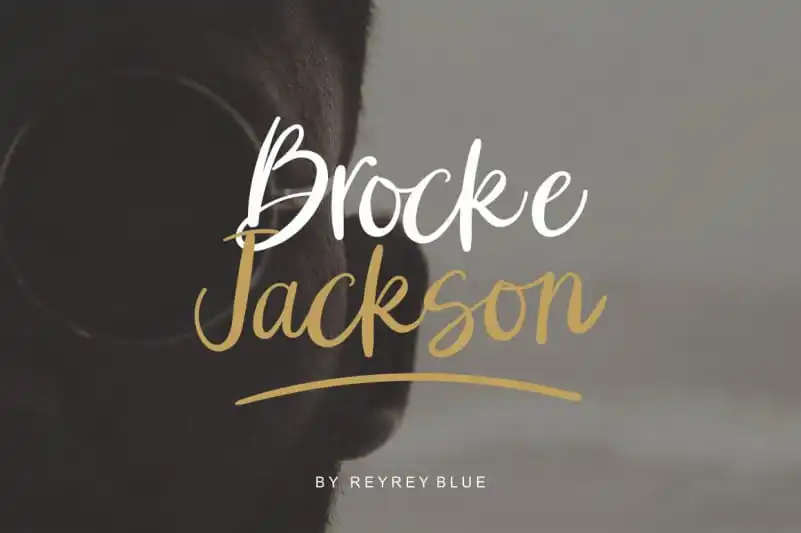
Brocke Jackson Script Font – Download Grátis
Brocke Jackson Script Font é uma elegante escolha para aqueles que buscam personalidade e elegância no seu design tipográfico. Desenvolvida pelo designer ReyreyBlue, esta fonte escritura expressa tem um toque de frescor ao combinar uma caligrafia cuidadosamente esculpida com a força de uma tipografia bold. Ideal para textos que exigem atenção e são marcantes na composição visual do seu design, como o logotipo ou o texto da sua página principal. Essa fonte incorpora uma personalidade única, ideal tanto para criações sóbrias quanto vibrantes, garantindo um toque autêntico e atraente em qualquer projeto que ela adere. Um ótimo exemplo é seu uso nas seções de destaque de páginas web ou como o texto principal em capas de livros, onde a simplicidade da tipografia se combina perfeitamente com a complexidade do estilo handwritten para criar um equilíbrio de beleza e identidade visual.